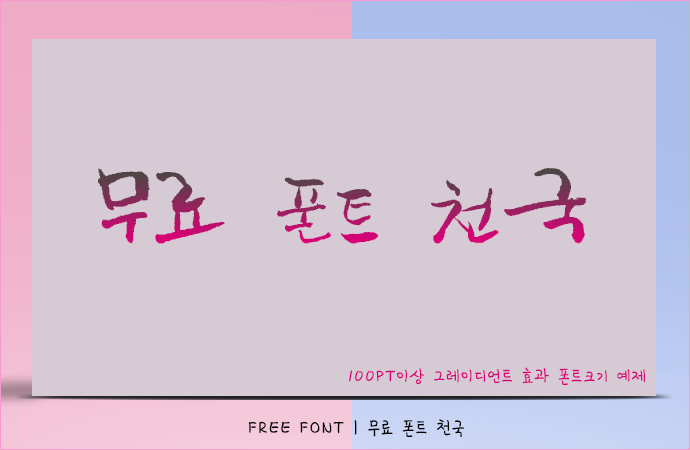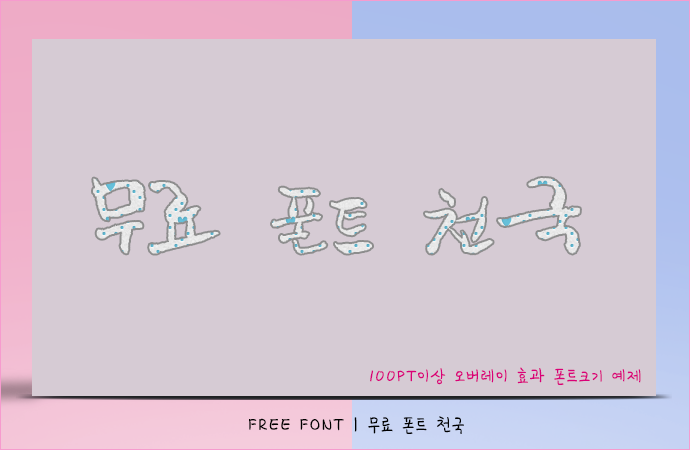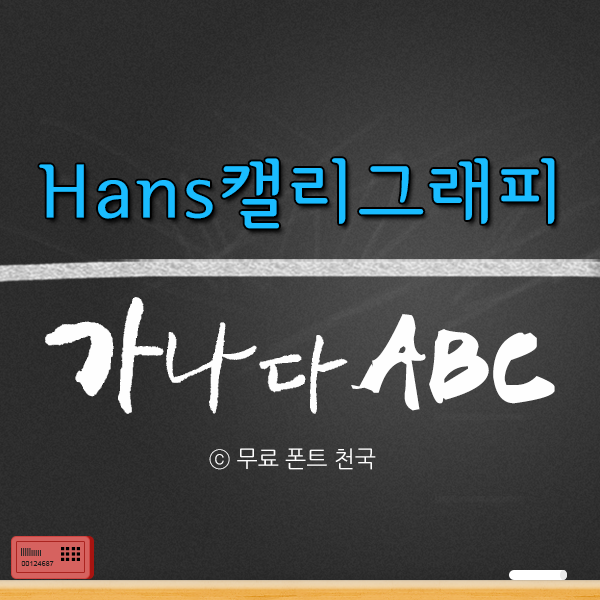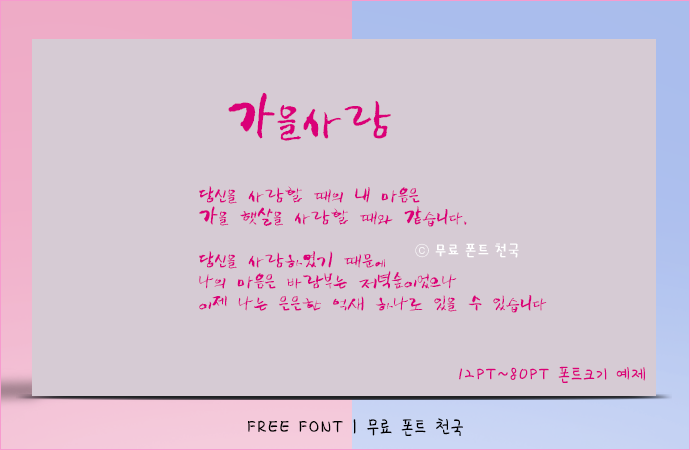
붓글씨 스타일의 HanS캘리그라피 폰트
Hans캘리그라피 폰트 정보
붓글씨 스타일의 Hans캘리그라피 폰트입니다. 붓글씨 서체의 느낌과 함께 휘갈겨 쓴 느낌을 함께 표현했습니다. 작은 글씨체에서는 가독성이 약간 떨어져 최소 12pt 이상에서 사용하길 권하고 있습니다. 본 폰트는 학교를 비롯해 공익 목적의 자선과 구호단체에서 제한 없이 사용 가능하며 개인 사용자의 경우 비상업적인 용도로 사용할 경우 자유롭게 이용 가능한 서체입니다.
Hans캘리그라피 폰트 # 미리보기
HanS캘리그라피 폰트, 12~80PT 크기로 적용한 효과
HanS캘리그라피 폰트, 100PT 크기 이상으로 작업한 오버레이 효과
HanS캘리그라피 폰트, 100PT 크기 이상으로 작업한 그레이언트 효과